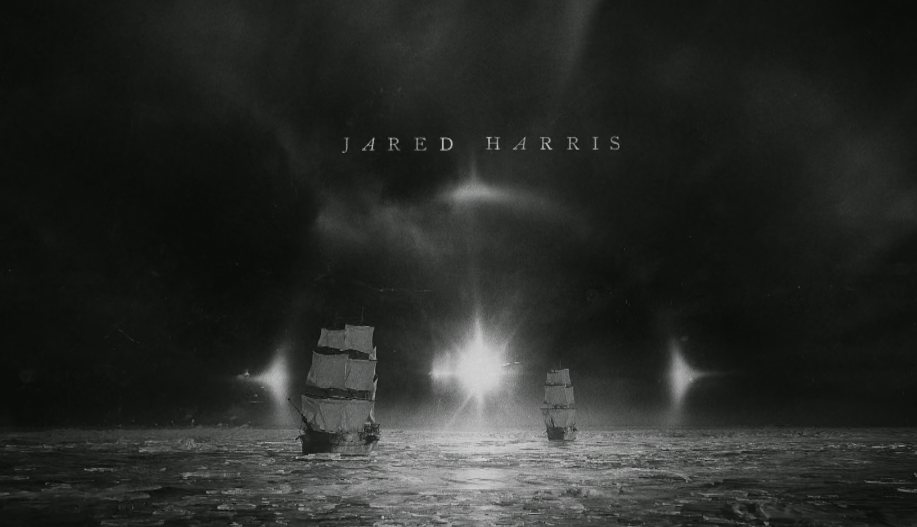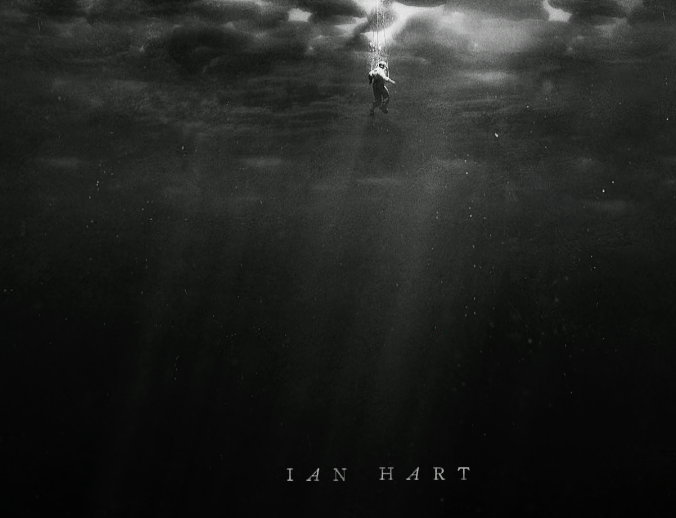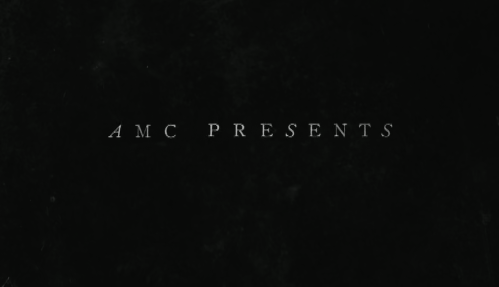
Suche Schrift aus dem Intro der Serie "The Terror" von 2018.
ich suche die originale Schriftart aus dem Vorspann der 2018 erschienenen Serie "The Terror" (Amazon Prime Video).
TFeld Mach mal bitte von der Schrift einen größeren screenshot. ich sehe das es eine serifenhafte mit kursiven Anteilen behaftete Schrift ist.
Mein tool der wahl ist z.B. find my font. gibt es auch als android app für mobile. ander sind das Eichhörnchen (fontsquirrl) etc. im Quellcode der webseite kann man nicht selten auch sehen welche schrift verwendet wurde, aber nicht immer. In PDFs ist in der Info auch immer der Font der verwendet wurde enthalten, sofern nicht nur bilder gemacht wurden. am Bsp. von typografie.info ist das mal gezeigt, was fmf gefunden hat. ich hoffe das bild ist selbst erklärend. wenn nicht auf der verlinkten seite ist das im video auch noch mal erklärt.